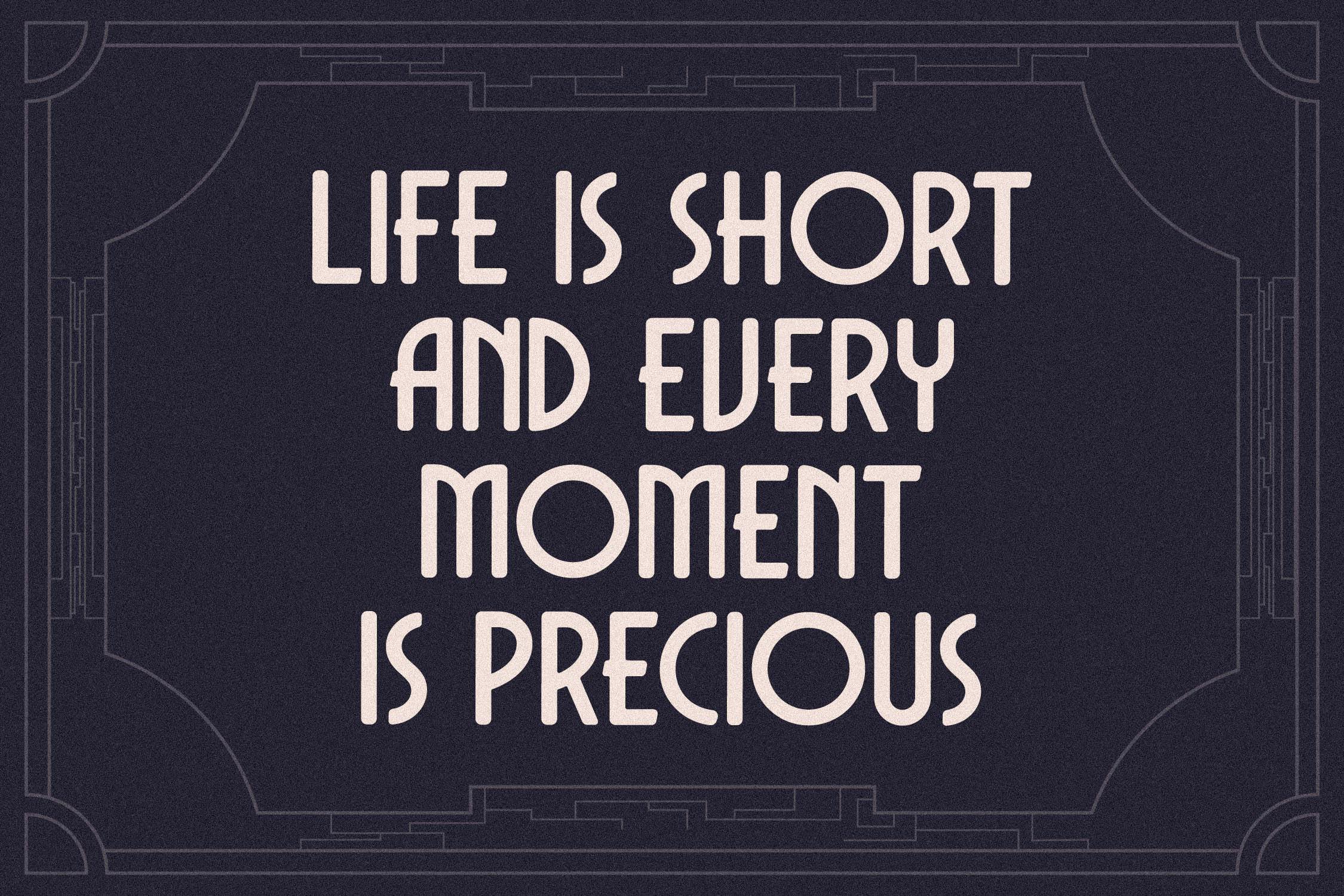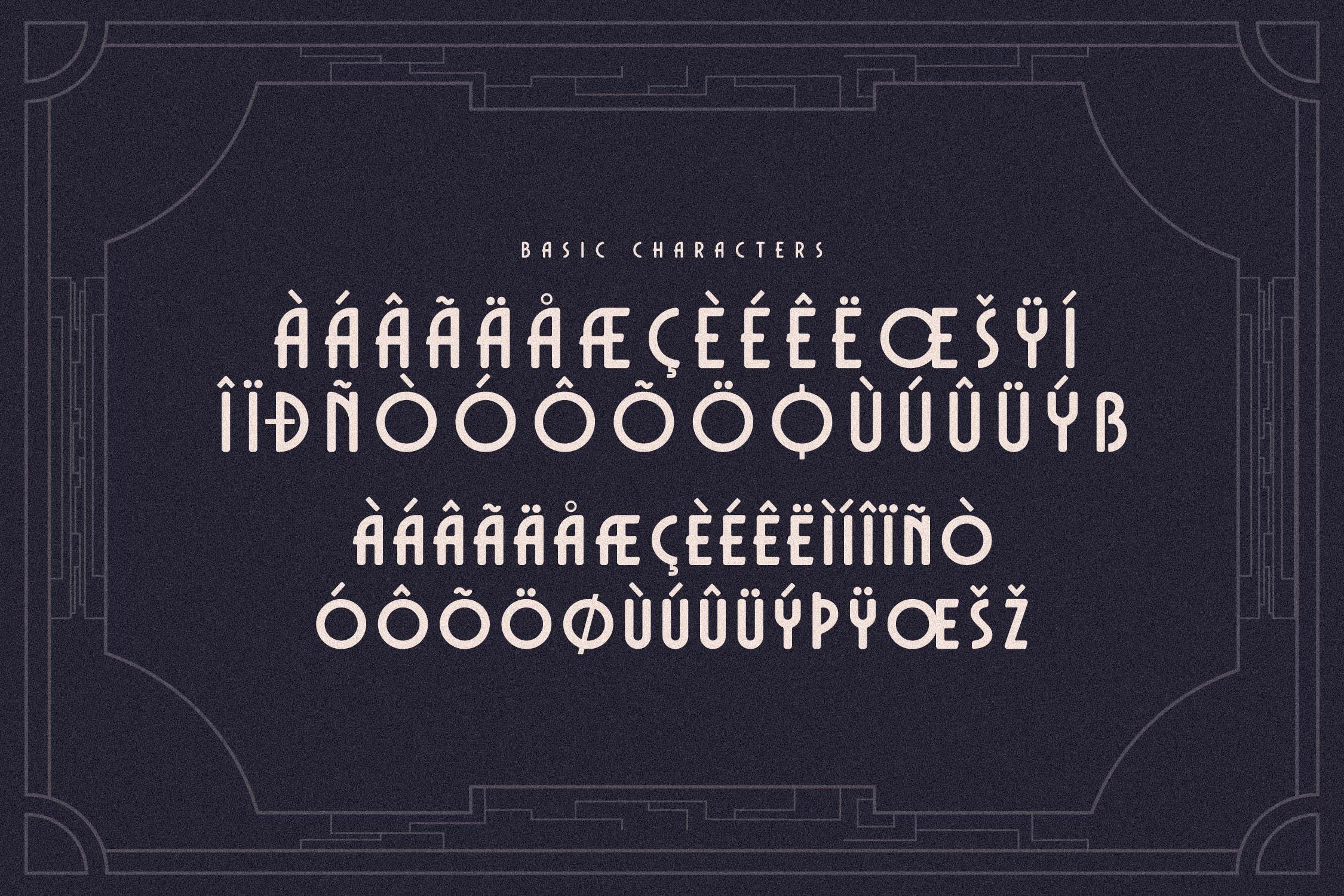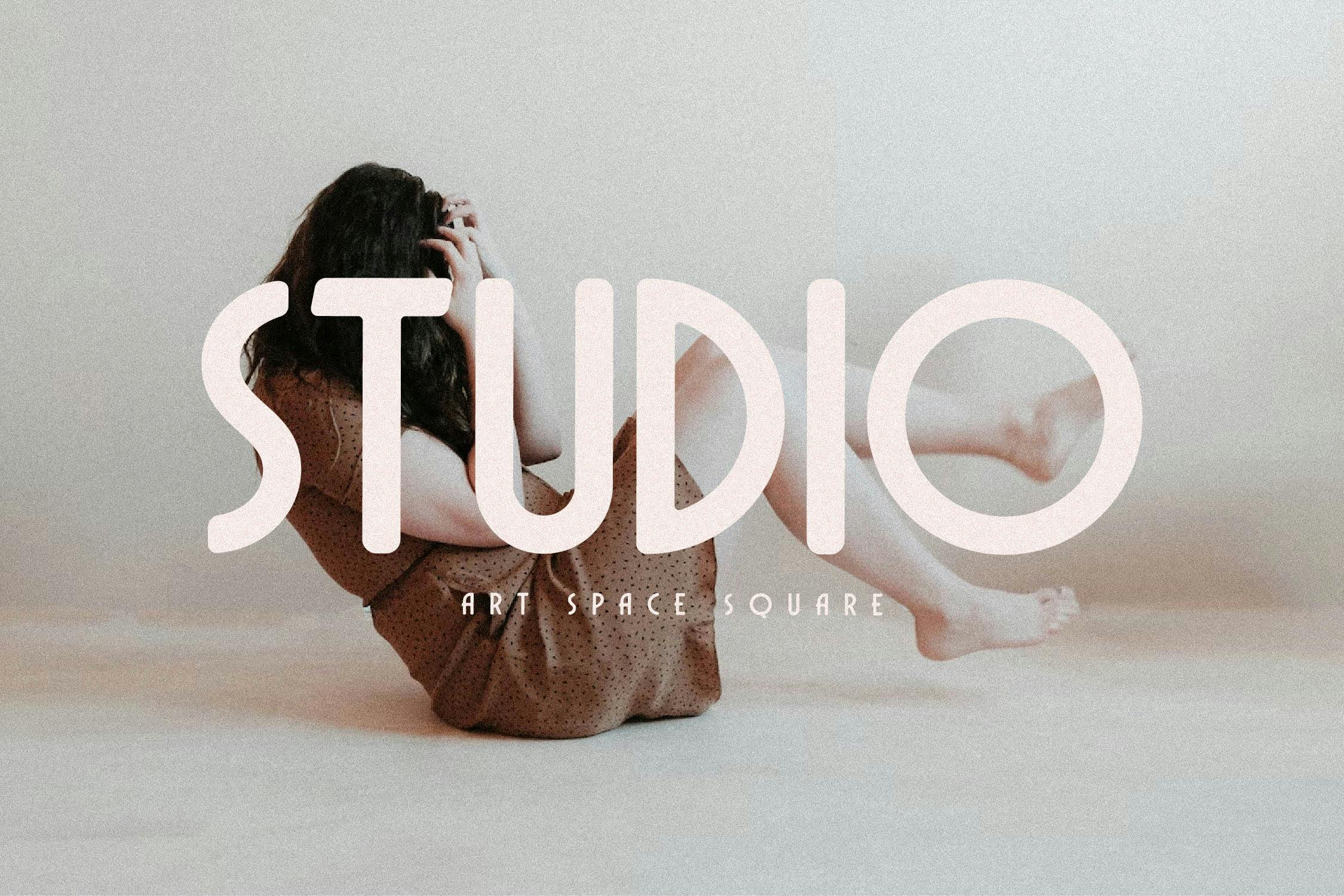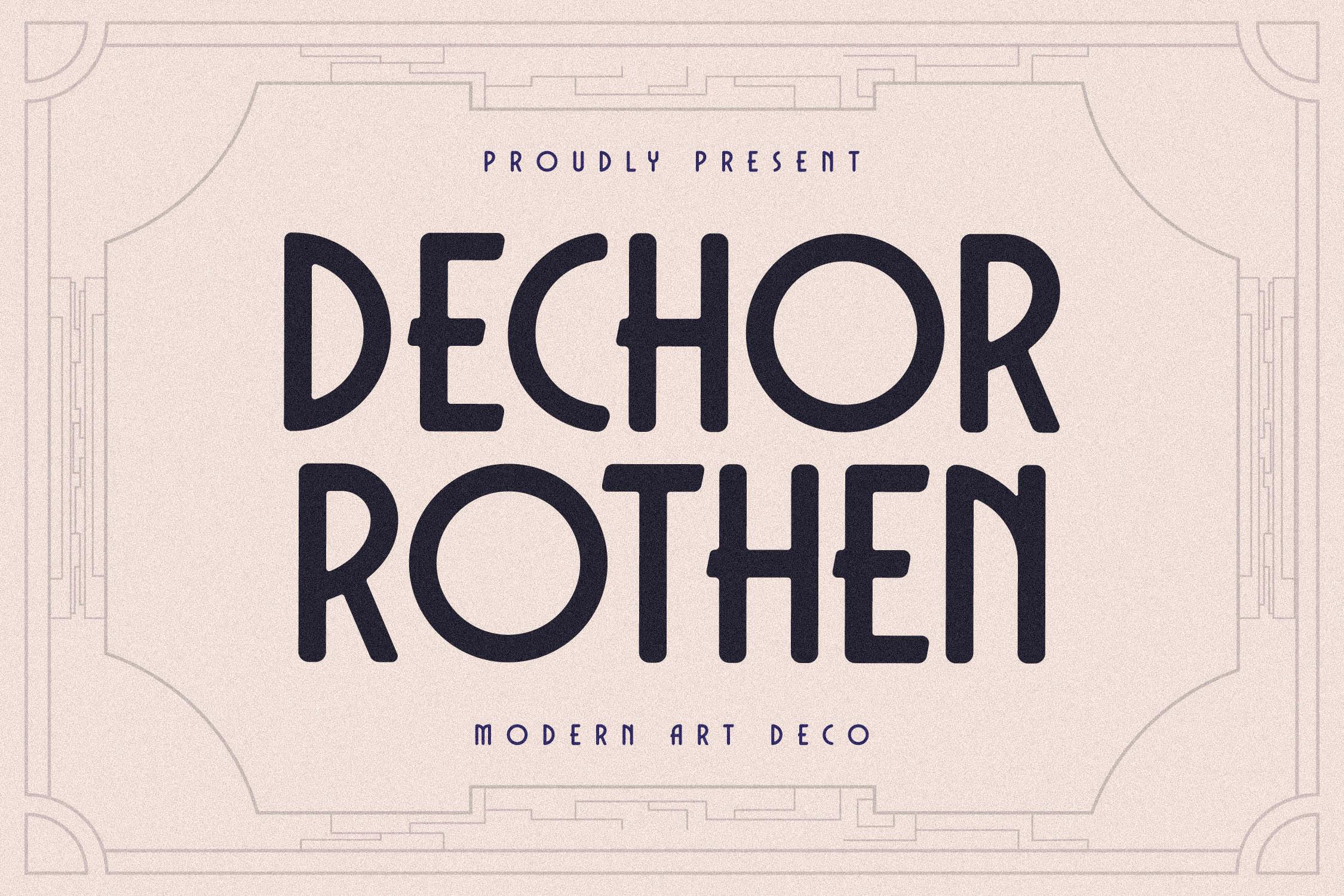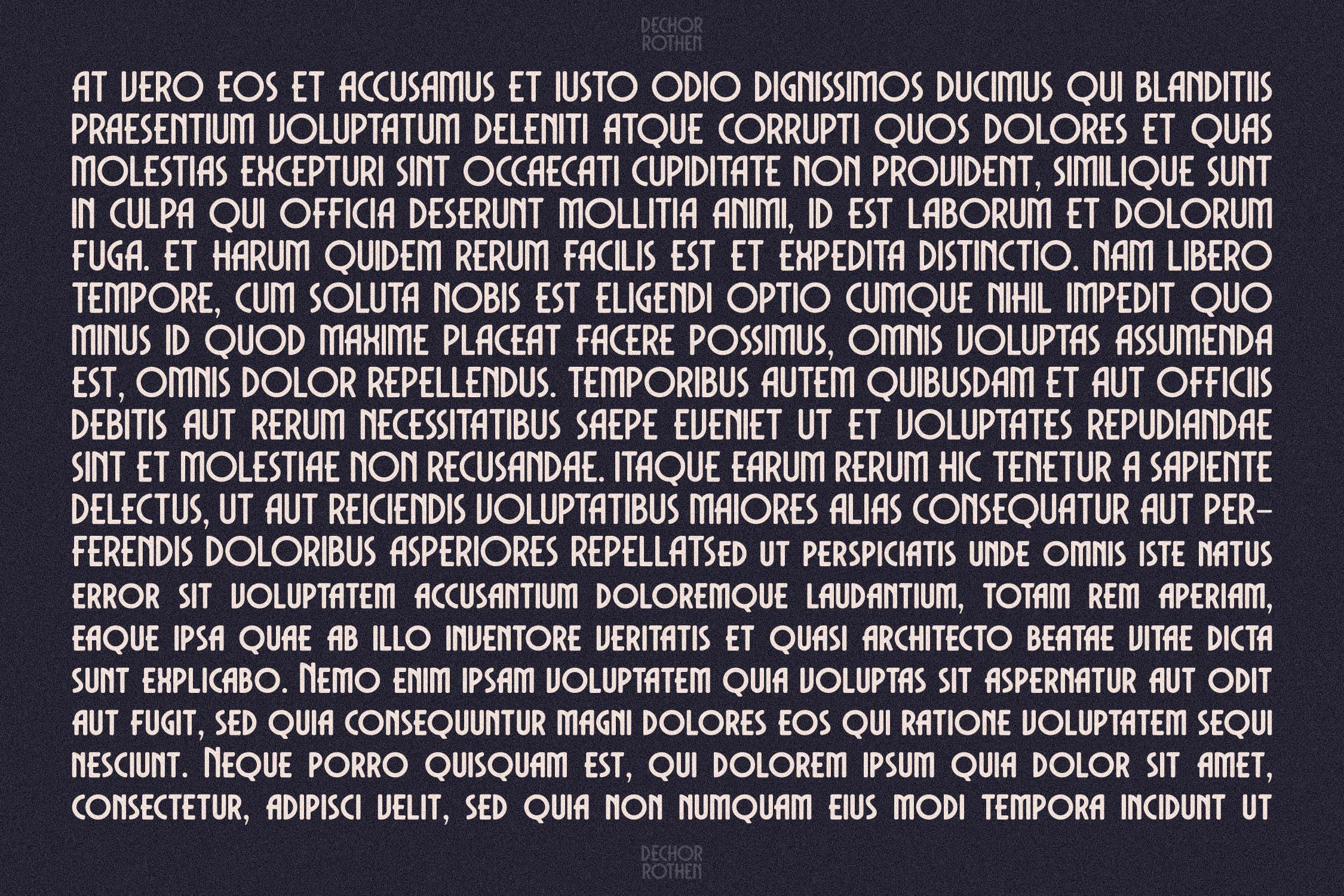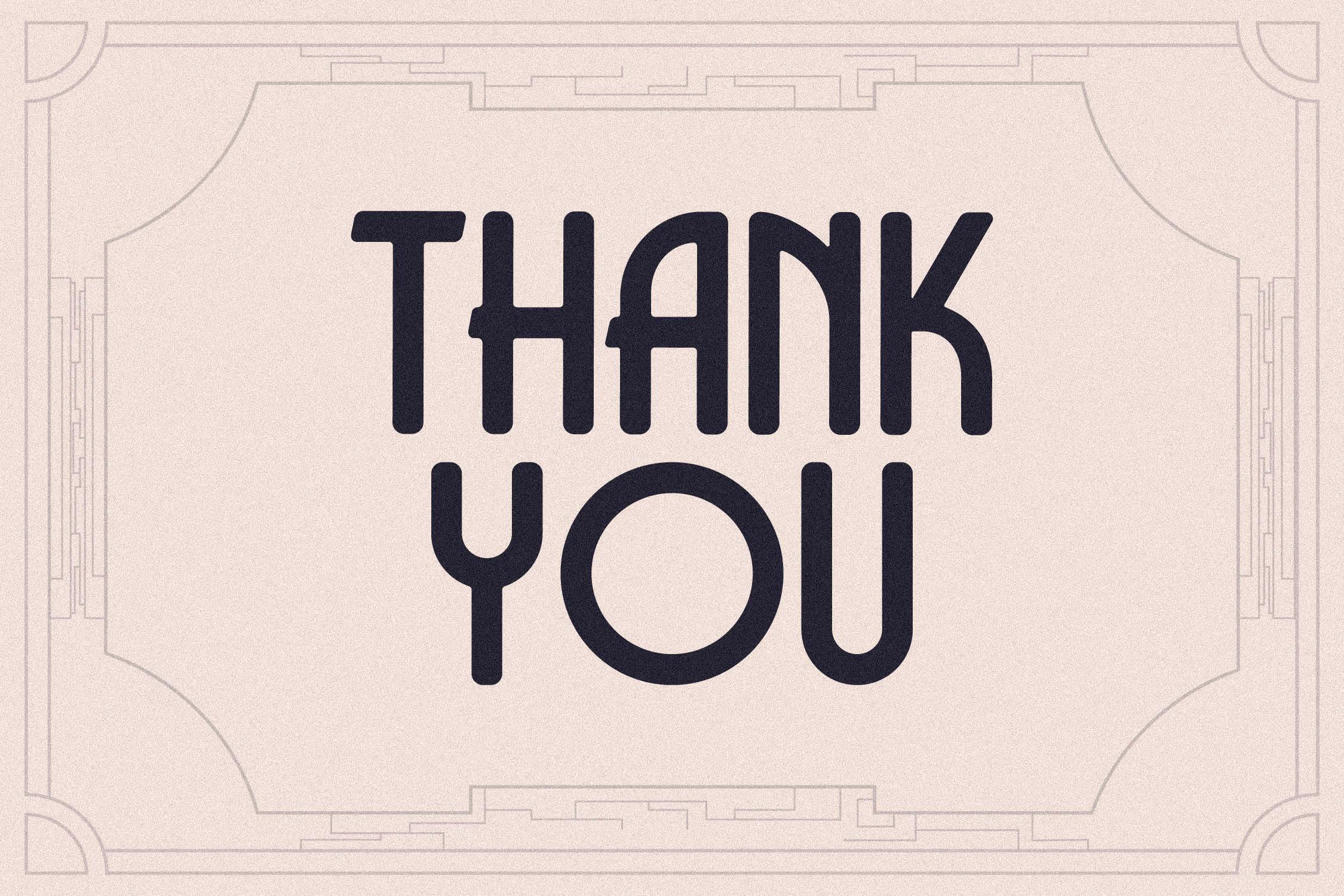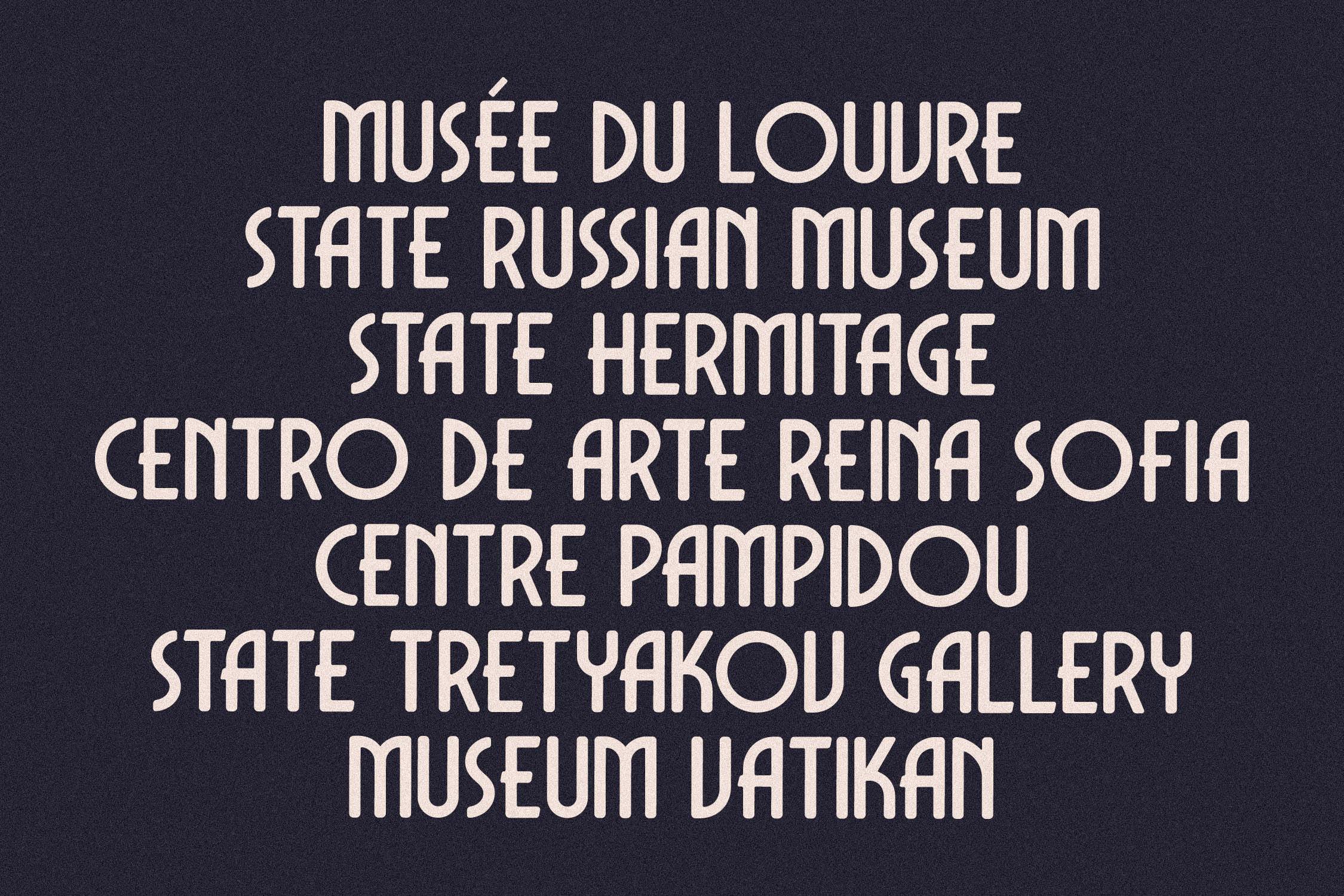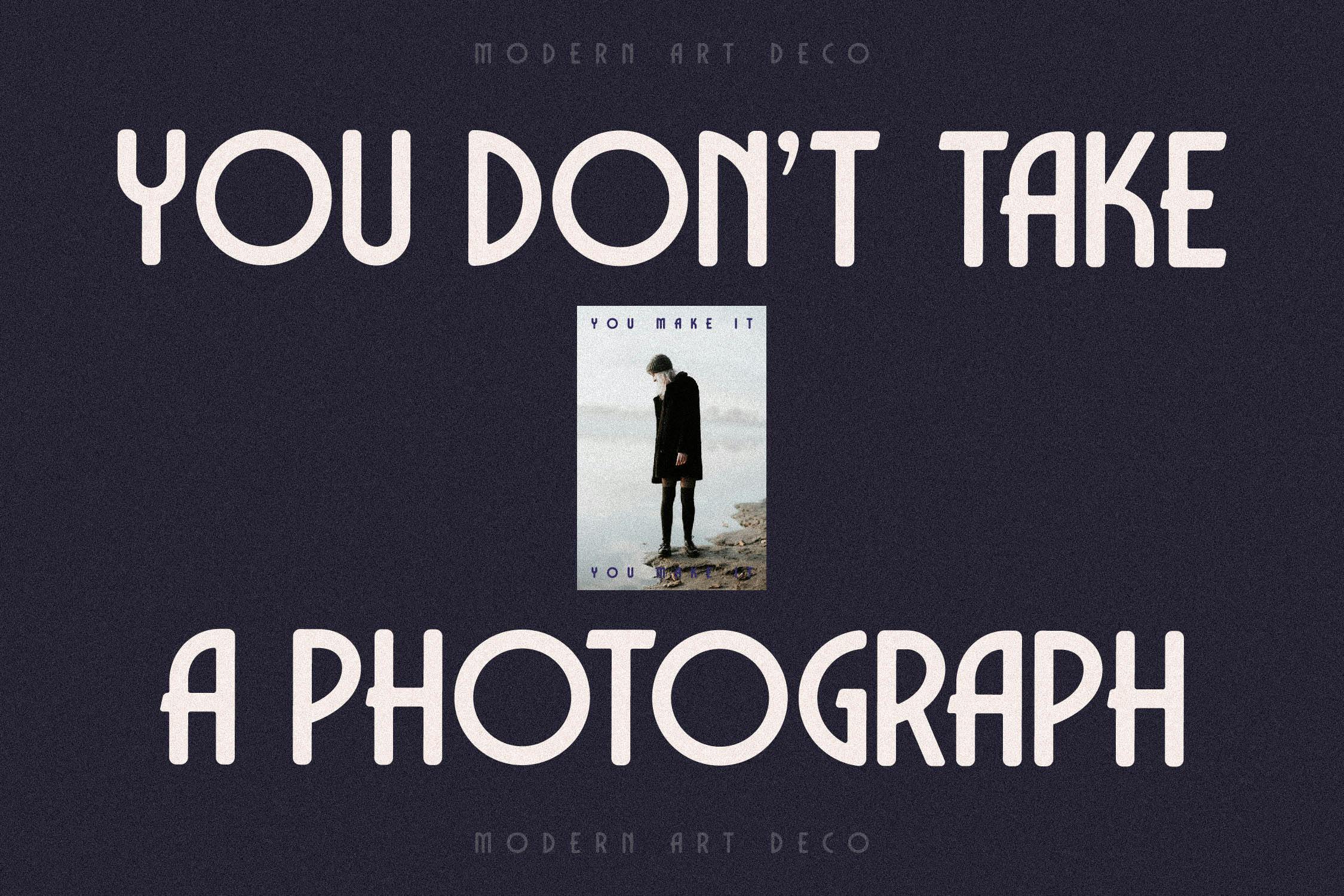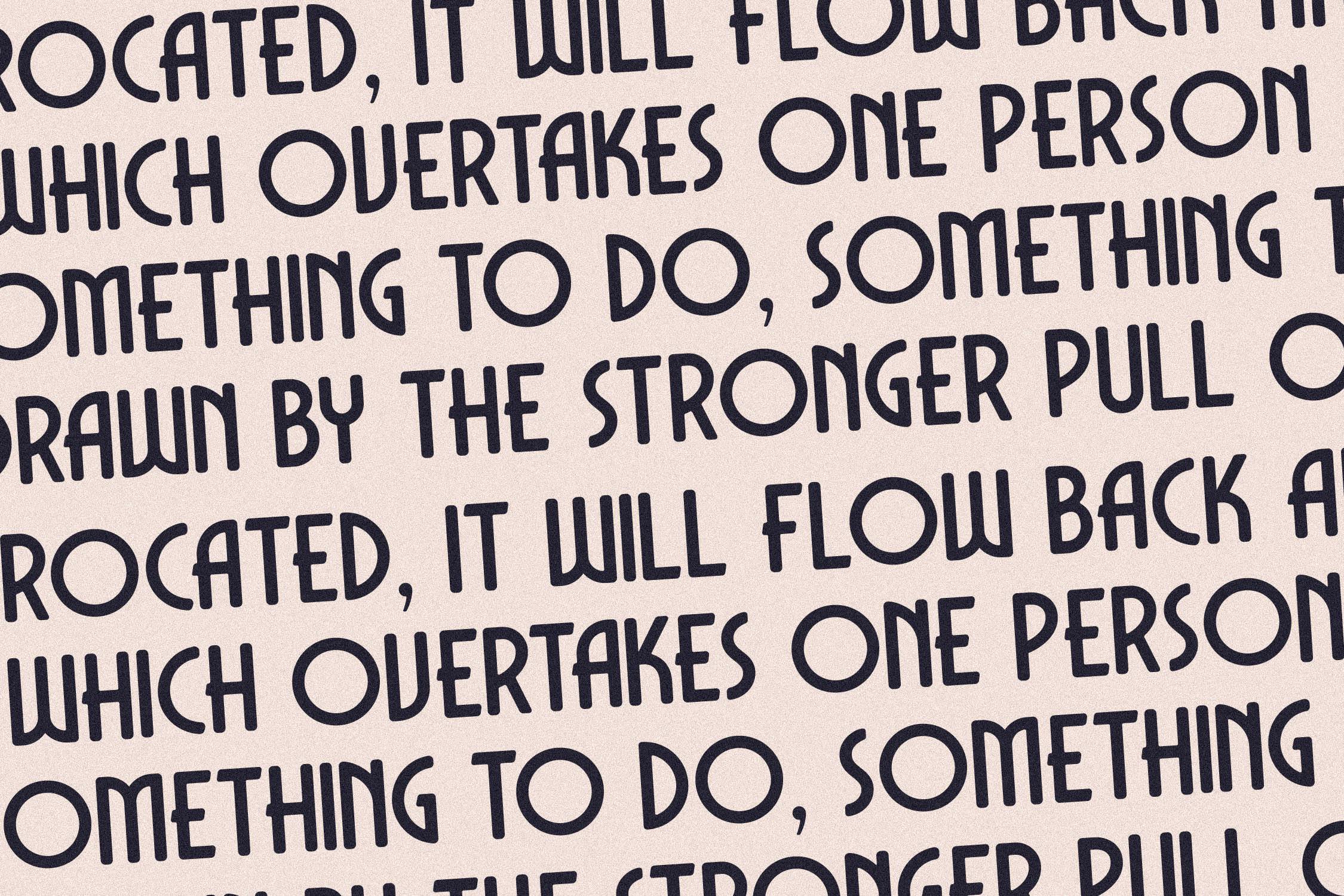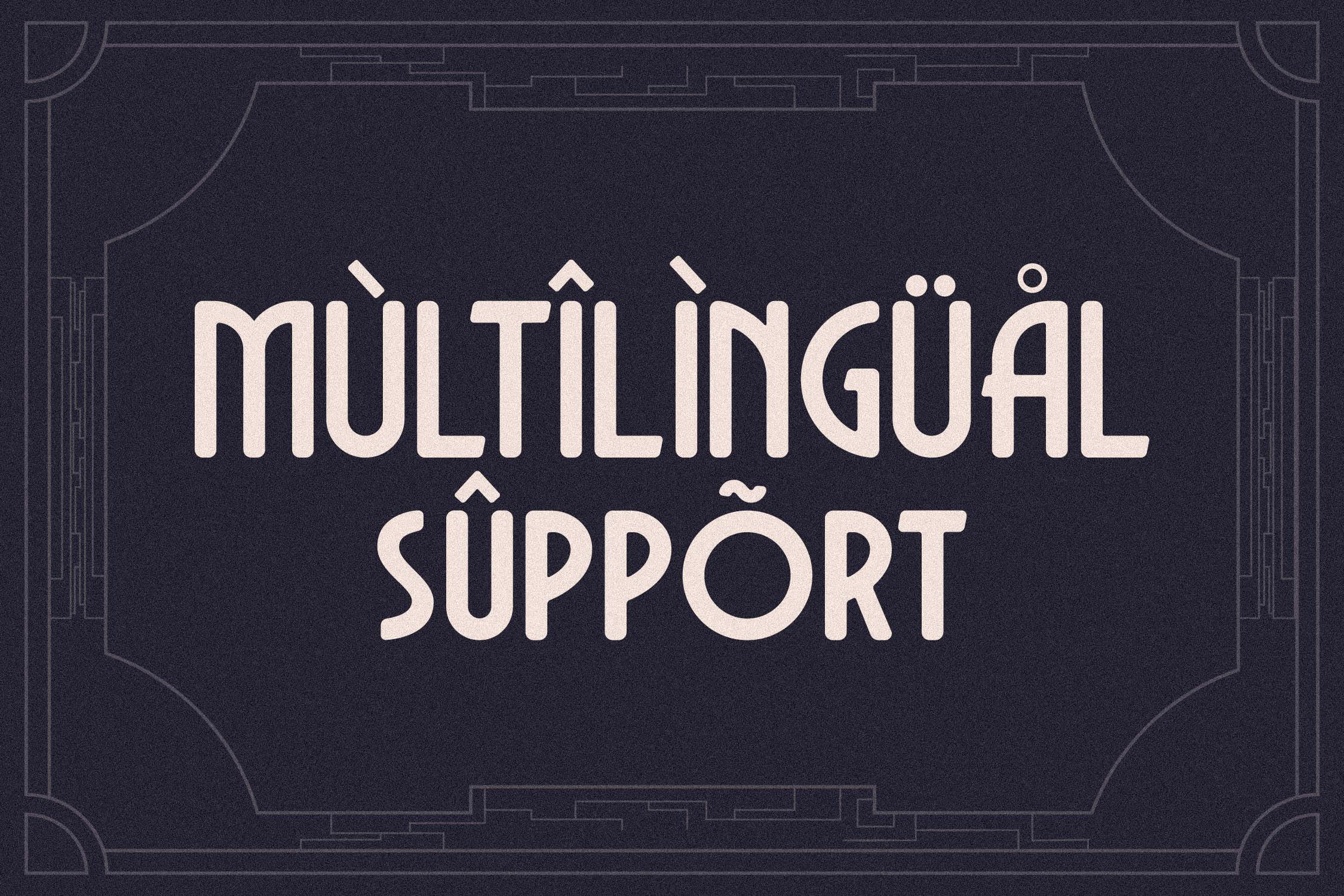
Dechor Rothen Modern Art Deco Font
فونت Dechor Rothen برای پروژه‌های خلاقانه دیجیتال و چاپی شما ایده‌آل است.
سلام خانم‌ها و آقایان، این یکی از فونت‌های ماست که برای تکمیل محصولات خلاقانه دیجیتال و چاپی شما مناسب است.
این فونت برای پوسترها، پست‌های شبکه‌های اجتماعی، برندینگ، پروژه‌های شخصی و غیره ایده‌آل است.